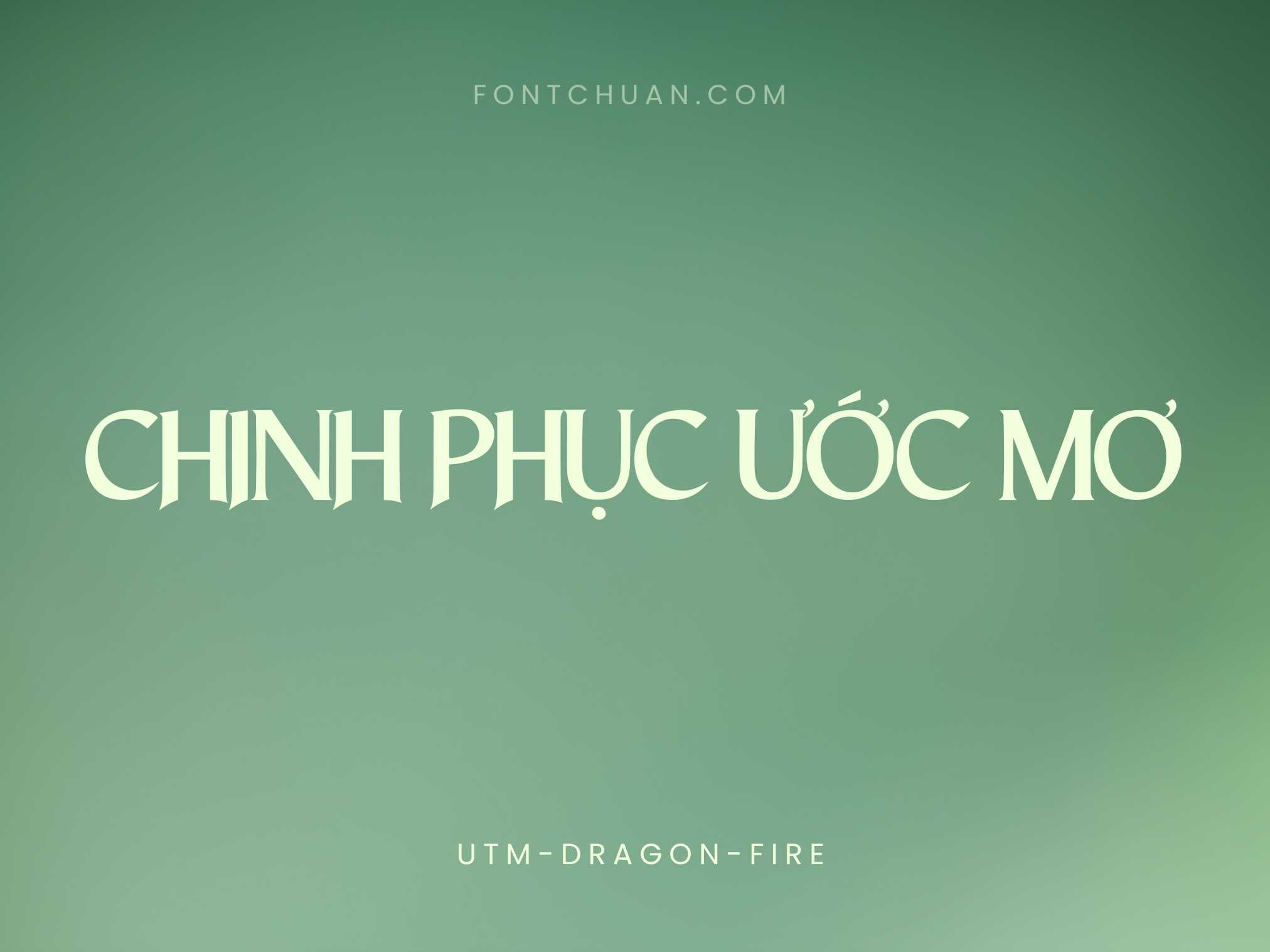
Font UTM Dragon Fire Việt Hóa
Font UTM Dragon Fire Việt Hóa là một kiểu chữ serif độc đáo, mang phong cách fantasy và huyền bí. Font gốc có tên là Dragon Fire, được sáng tạo bởi Girinesia. Với các đường nét sắc sảo, mạnh mẽ và mang hơi hướng rồng lửa, font này kết hợp phong cách Font Gothic với các yếu tố Font cổ trang, tạo nên sự huyền bí, quyền lực và cổ điển. Nhờ vậy, UTM Dragon Fire là lựa chọn hoàn hảo cho các thiết kế mang phong cách kỳ ảo, thần thoại, trò chơi và các dự án mang hơi hướng lịch sử hoặc truyền thuyết.
Font này đã được Việt hóa để hỗ trợ đầy đủ tiếng Việt bởi Đinh Kiên, ngoài ra còn hỗ trợ nhiều ngôn ngữ khác. Thành viên của Font Chuẩn đã sưu tầm và chọn lọc font này nhằm đáp ứng nhu cầu của người dùng trong thiết kế và ứng dụng thực tế. Font có đặc điểm nổi bật với các nét chữ gai góc, thể hiện sự mạnh mẽ và huyền bí, phù hợp với các dự án như bìa sách, poster, logo game và nhiều lĩnh vực sáng tạo khác.